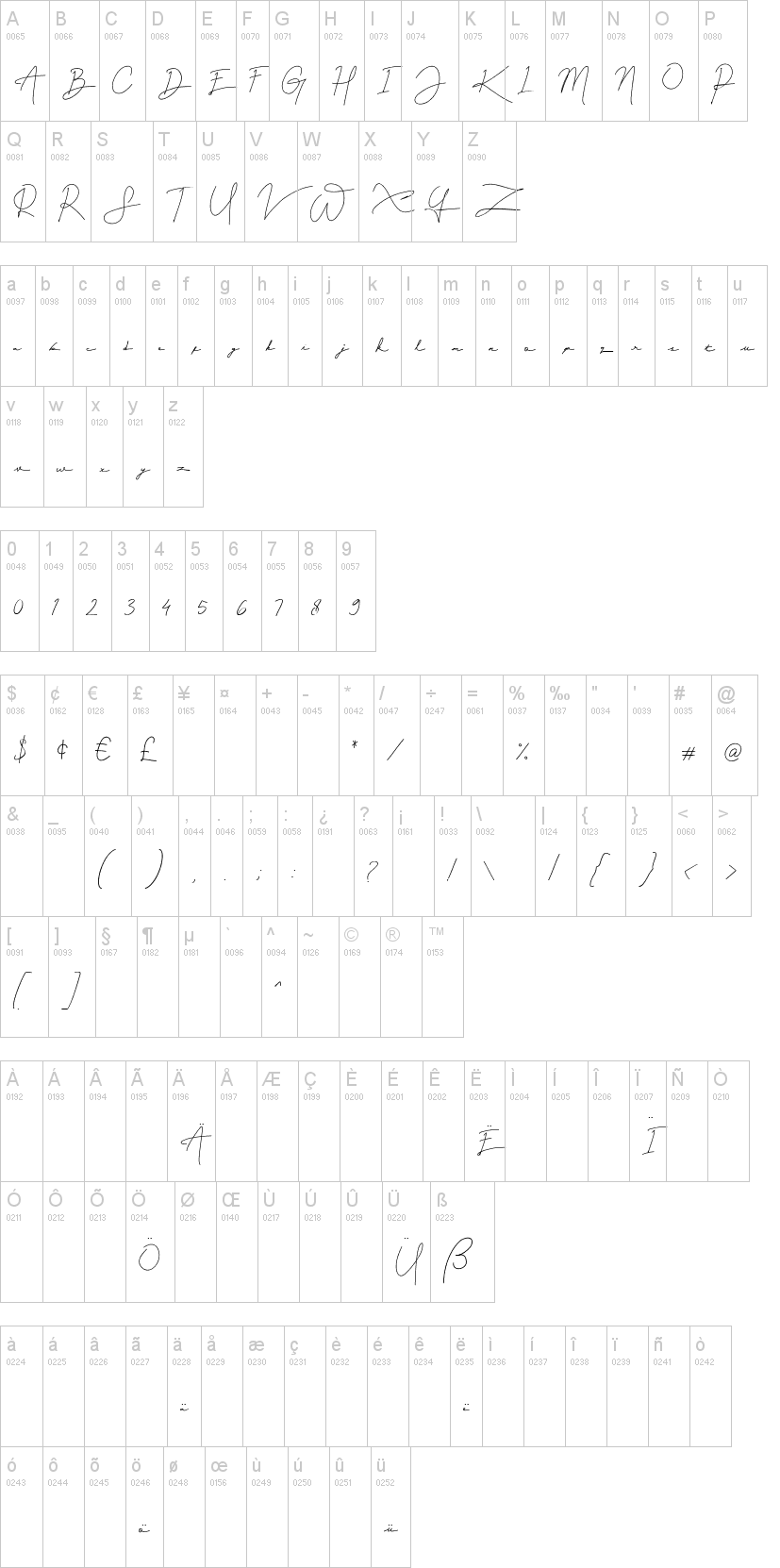
Gellattik Janggan 是一款受到传统印度手绘字体启发而创作的欧洲字体。字体具有细节丰富的线条,精致的笔画,以及明快的色彩。它的字形设计灵活,可以用于各种类型的文本,从报纸标题到海报标语,从文字图标到漫画书,都能让文字充满生机和活力。Gellattik Janggan 可以用于各种类型的文字,无论是印刷文字还是电子文字,都能让文字充满生机和活力。内容介绍
Gellattik Janggan是一款非常不错的手写艺术字体,具有很好的视觉感,适合于文化类的宣传设计、商业类品牌的广告和产品包装设计以及个性化文字排版等较多场景。